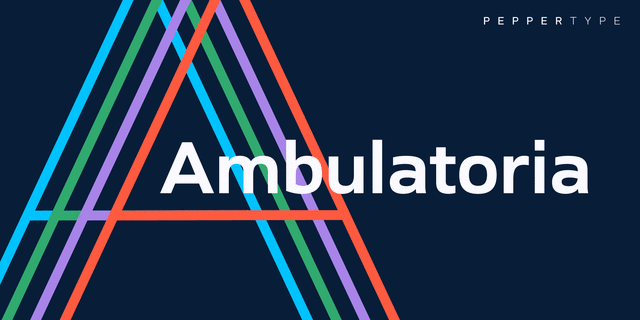
Ambulatoria C – третій із чотирьох наборів супергарнітури.
Ambulatoria – це міцний шрифт без засічок із відкритою апертурою, представлений у чотирьох варіантах. Кожен варіант: A, B, C і D містить альтернативні варіанти для певних гліфів, які дозволяють дизайнеру змінювати характер і текстуру шпальти.
Ця супергарнітура містить 80 накреслень, кожне з яких має багату мовну підтримку, включно з загальноєвропейською латинкою та кирилицею. Шрифт призначений для роботи з текстами як великого, так і маленького розміру, що робить Ambulatoria універсальною робочою конячкою.
Шрифт розробив Олег Ліщук у 2022 році.